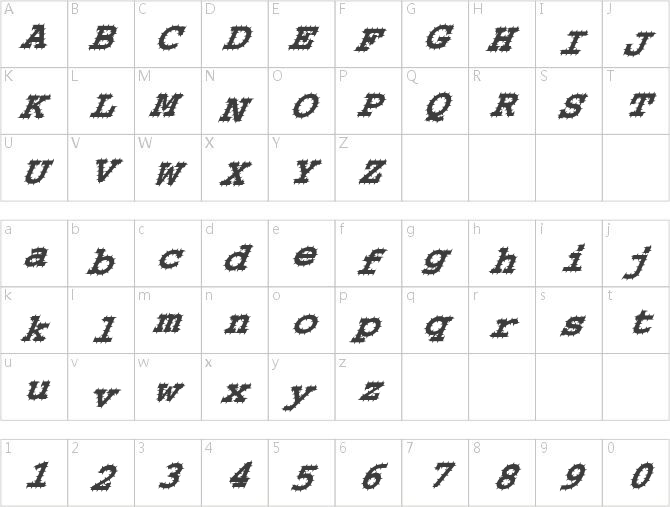
FZ BASIC 54 SPIKED ITALIC 詳情頁
FZ BASIC 54 SPIKED ITALIC字體字庫是一款讓人賞心悅目、百看不厭的英文字體,適合各類廣告和產(chǎn)品包裝設(shè)計應(yīng)用,字體大小0.1MB,格式為ttf字體,上傳用戶是文生電腦,作者/版權(quán)方為未知